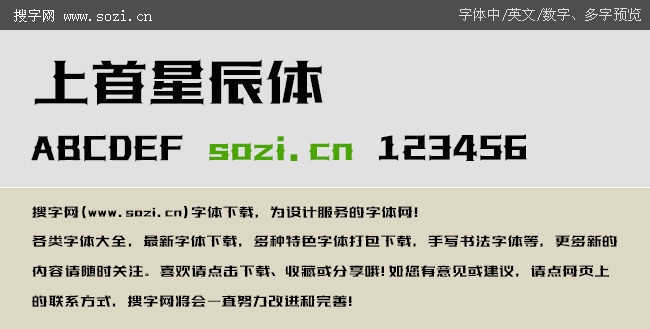
上首星辰體
搜字網(wǎng)給大家提供一款上首星辰體中文字體下載,上首星辰體字體字體筆畫規(guī),筆畫整體采用規(guī)整的幾何形狀,整體給人一種穩(wěn)重踏實(shí)的感覺(jué),在筆畫的末端處做曲線尖角的襯飾處理,增加了字體整體的美感。適用于搭配標(biāo)志、廣告標(biāo)語(yǔ)、商業(yè)廣告等廣告設(shè)計(jì)。